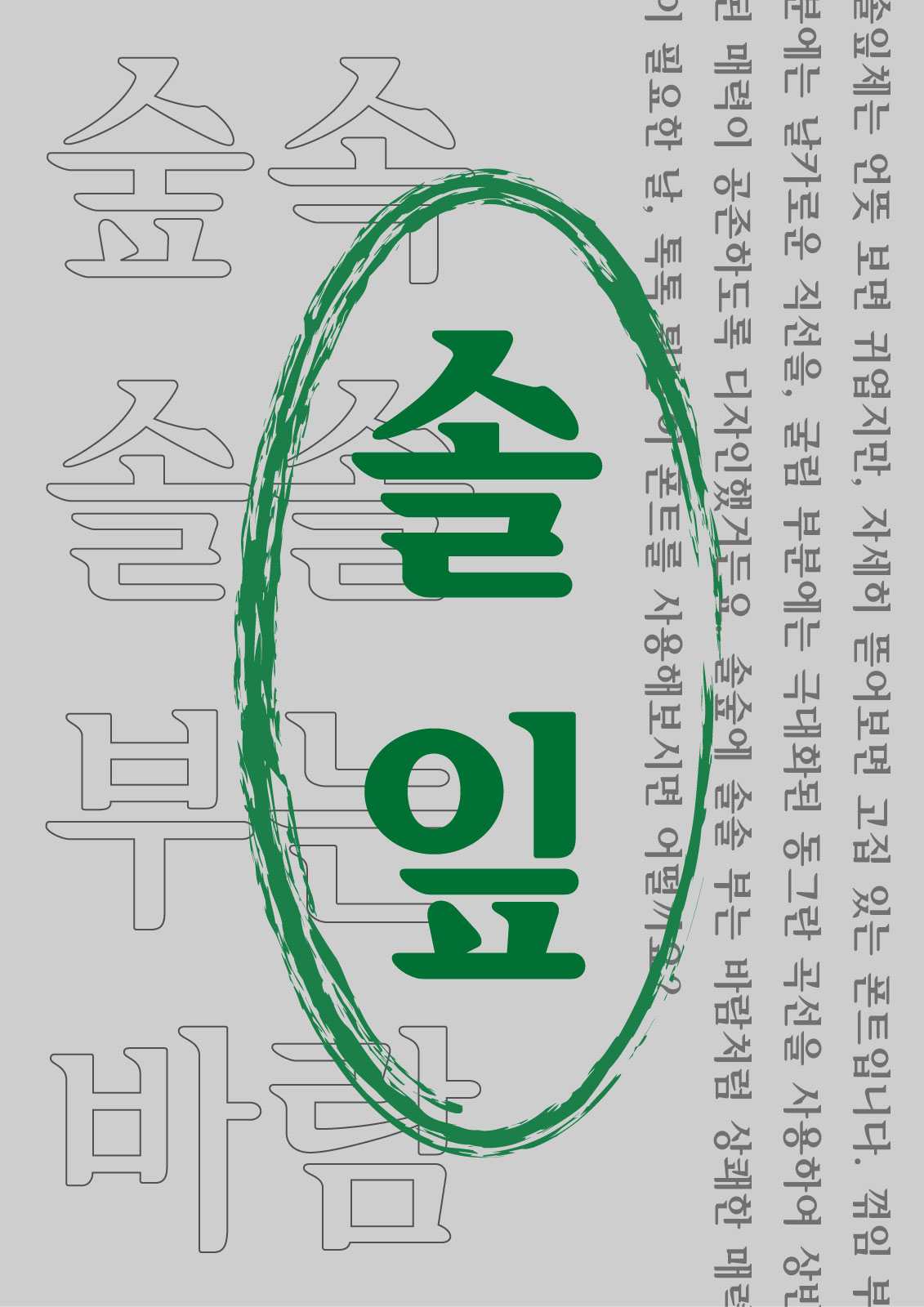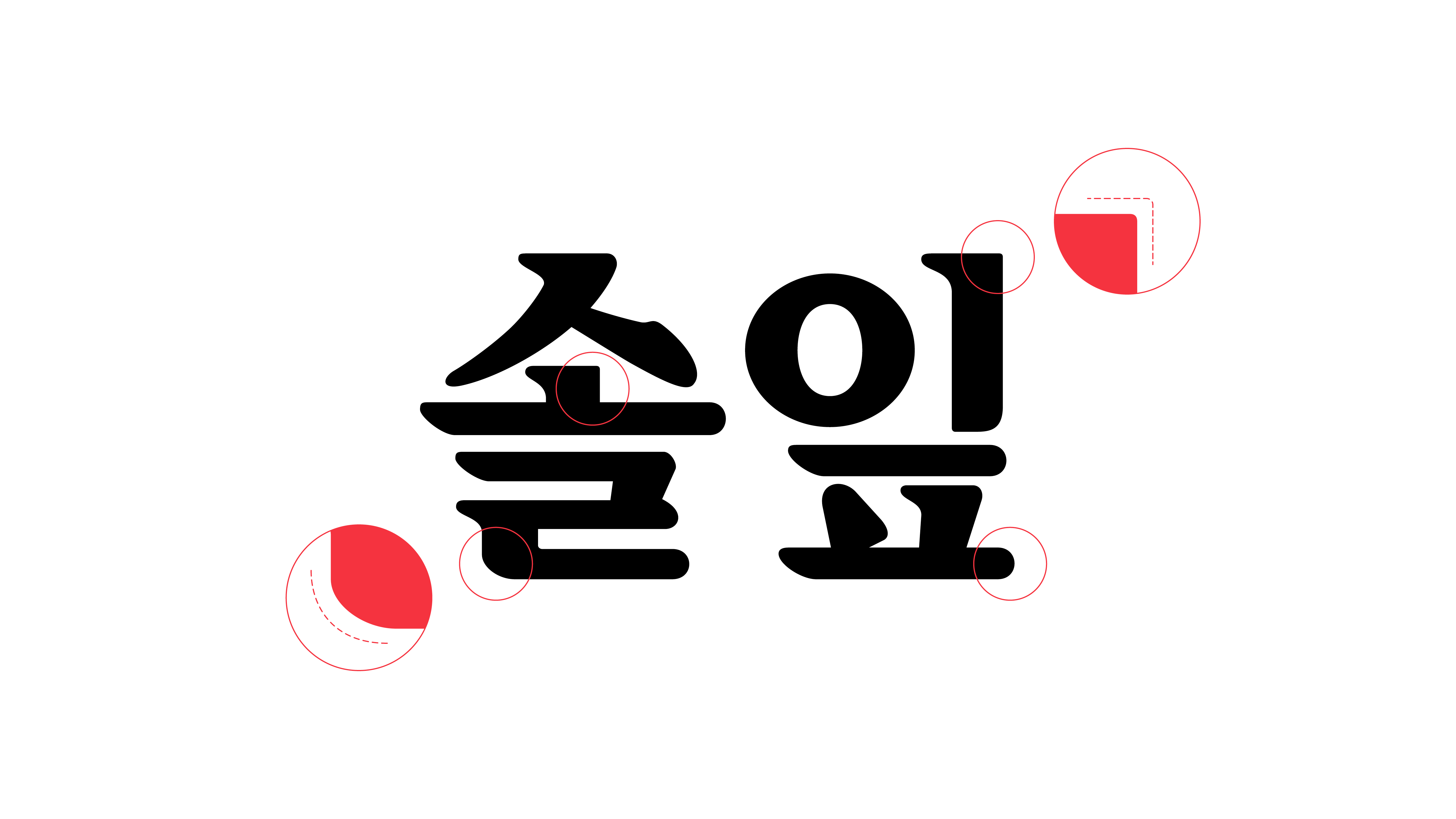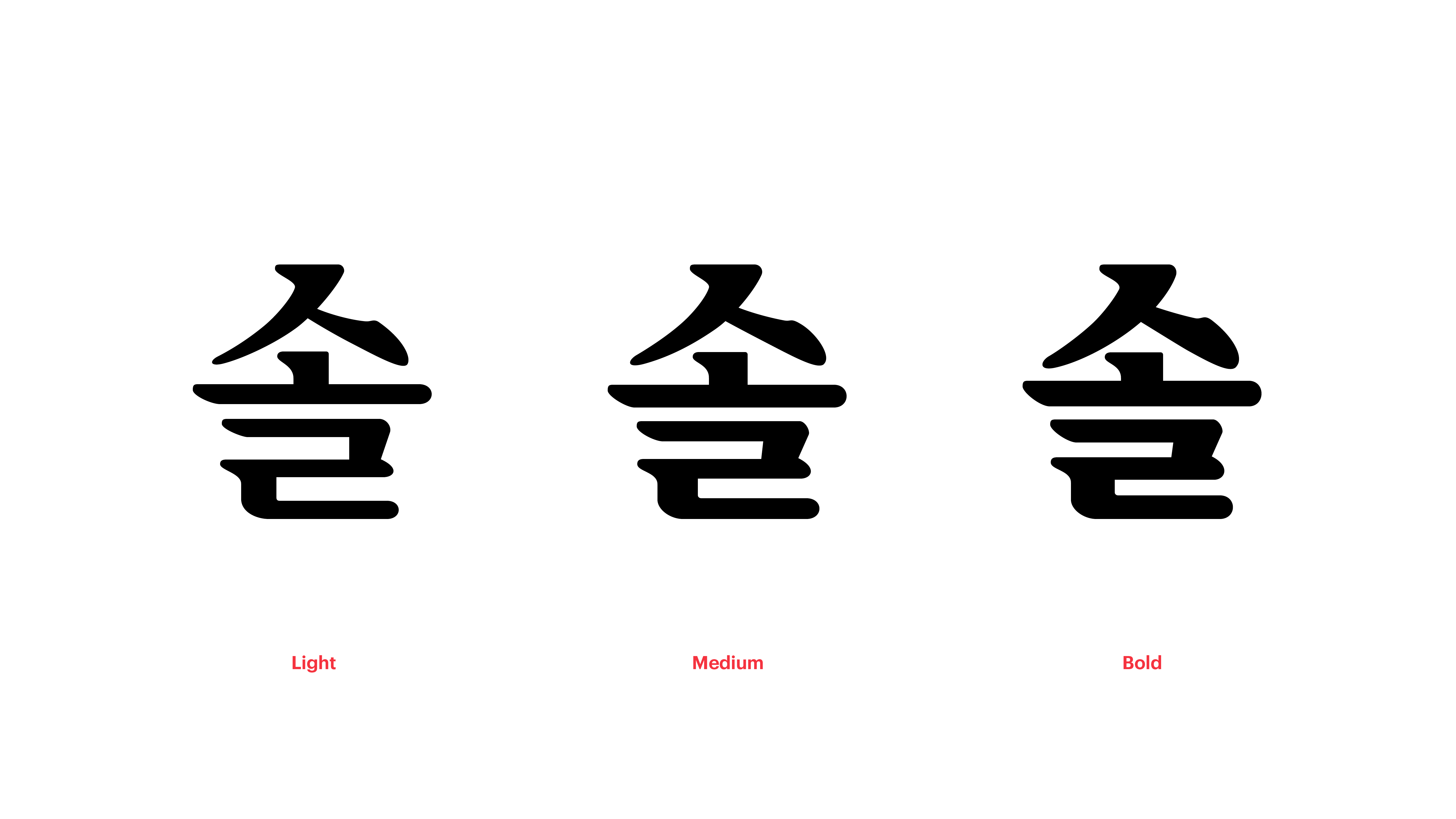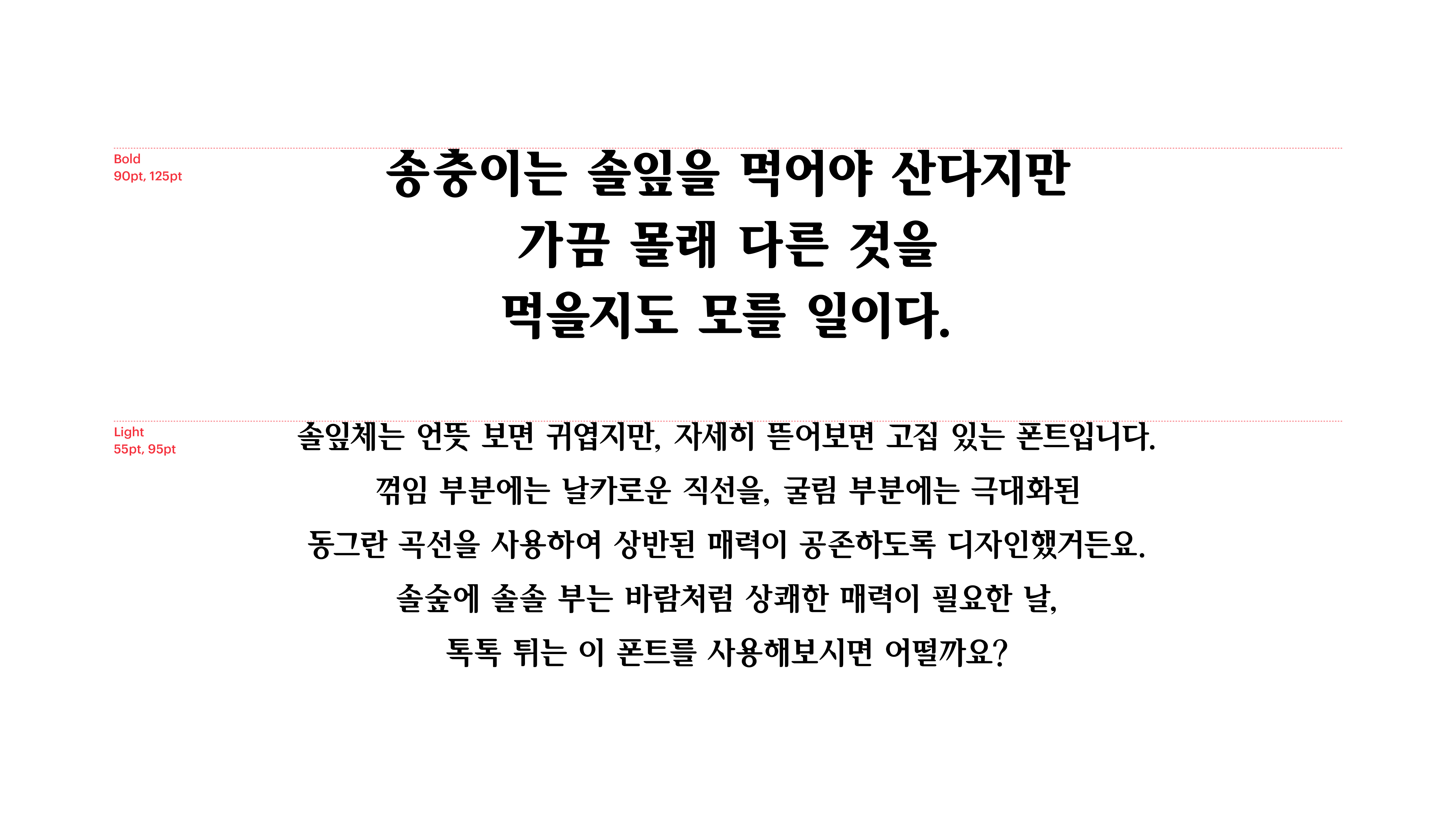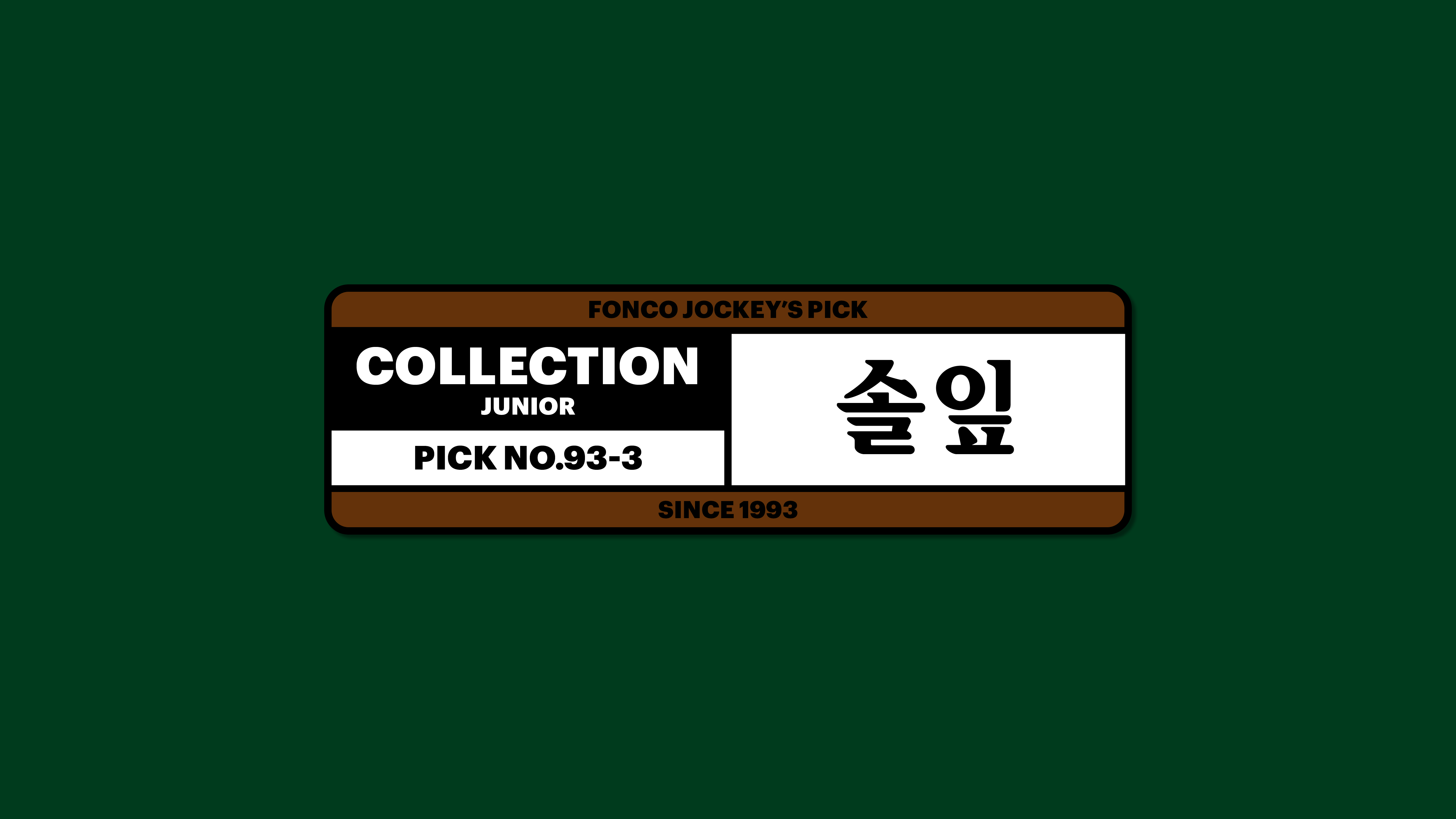
솔잎
Yoon 솔잎
솔잎체는 언뜻 보면 귀엽지만, 자세히 뜯어보면 고집 있는 폰트입니다. 꺾임 부분에는 날카로운 직선을, 굴림 부분에는 극대화된 동그란 곡선을 사용하여 상반된 매력이 공존하도록 디자인했거든요. 솔숲에 솔솔 부는 바람처럼 상쾌한 매력이 필요한 날, 톡톡 튀는 이 폰트를 사용해보시면 어떨까요?